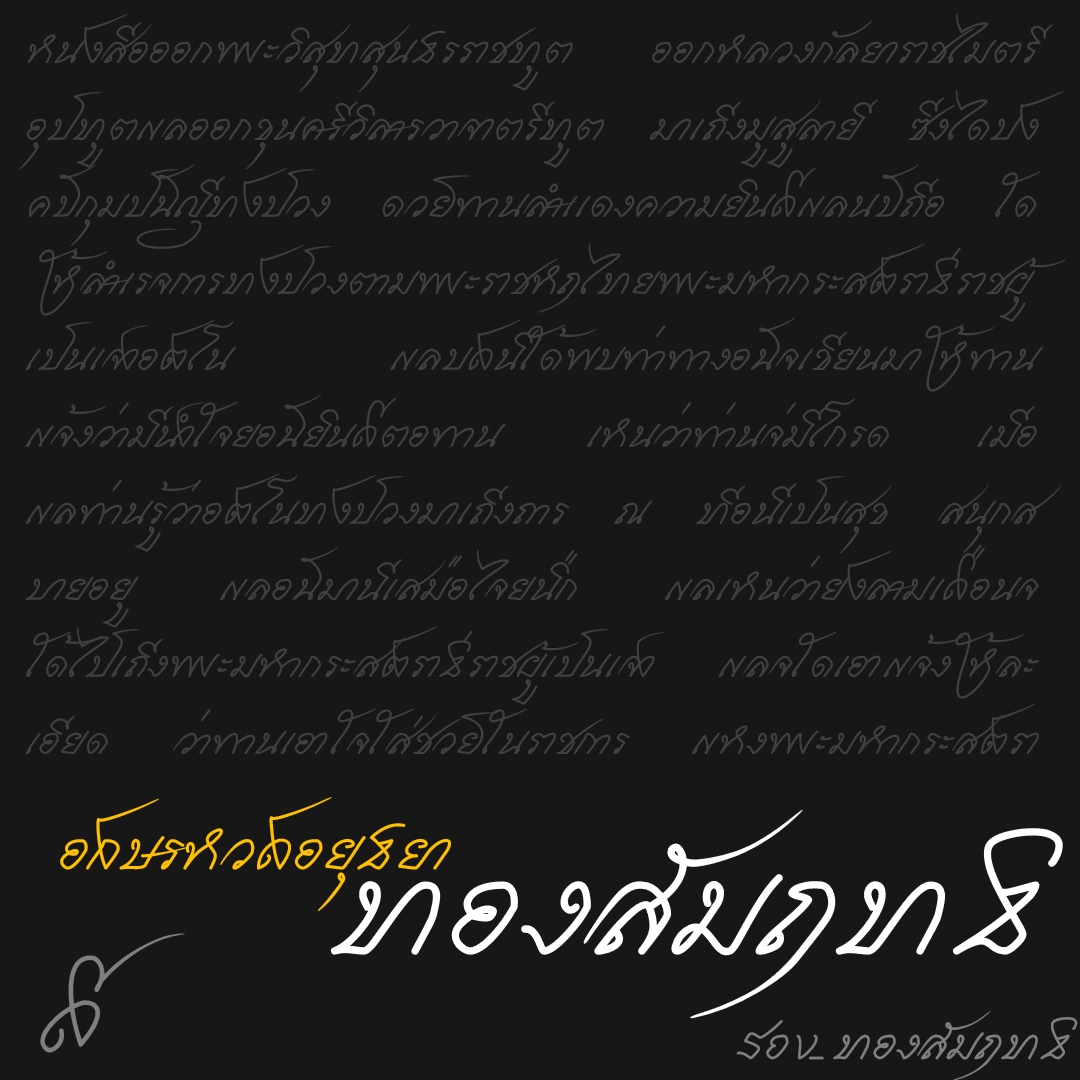
ฟอนต์ ทองสัมฤทธิ์
ฟอนต์ทองสัมฤทธิ์ ได้แนวคิดจากอักษรหวัด สมัยอยุทธยา โดดเด่นที่การรวบอักษร เชื่อมอักษร พยัญชนะ-พยัญชนะ พยัญชนะ-สระ พยัญชนะ-วรรณยุกต์ สระ-วรรณยุกต์ นอกจากนี้ยังมีการใช้พยัญชนะเดียวประสมสองรูป เช่น ในี (ในนี้) และอื่นๆ
ถ้าเอามาใช้กับแพนแกรม
ชื่อฟอนต์ : ทองสัมฤทธิ์
ฟอนต์ทองสัมฤทธิ์ ได้แนวคิดจากอักษรหวัด สมัยอยุทธยา โดดเด่นที่การรวบอักษร เชื่อมอักษร พยัญชนะ-พยัญชนะ พยัญชนะ-สระ พยัญชนะ-วรรณยุกต์ สระ-วรรณยุกต์ นอกจากนี้ยังมีการใช้พยัญชนะเดียวประสมสองรูป เช่น ในี (ในนี้) และอื่นๆ
คหสต.  อักษรตัวหวัดส่วนใหญ่เป็นการเขียนจากดินสอบนกระดาษถึงจะตวัดได้ จากอยุธยา 300ปีกว่า จะเหลือมาถึงปัจจุบันนั้นยากมาก เนื่องด้วยสภาพอากาศร้อนชื้นแบบบ้านเรา รวมถึงมอดปลวกอีก  หลักฐานที่พบได้มักอยู่ในที่อากาศเย็น เช่น ยุโรป และจีน ครับ
ลำดับการเขียนพวกไม้หันอากาศมีตัวสะกดนี่
เขาเขียนตัวสะกดก่อน แล้วค่อยเติมไม้หันอากาศข้างบนเหรอครับ
(รวมถึงการใส่เสียงวรรณยุกต์ของคำด้วย)
แล้วเวลาพิมพ์ต้องลำดับแบบนั้นไหมครับ
ตอนที่ทำฟอนต์ ก็มีคำถามนี้เหมือนกันครับ  เลยเอาตัวเองเป็นที่ตั้งว่า ถ้าเราจะเขียนคำว่า
- "ข้าพเจ้า" แบบเร็วๆ การเขียนไม้โท สระอา ช้ากว่า สระอา-ตวัดหางขึ้น  ผมก็จะเขียน ข สระอา-ตวัดหาง
- "ด้วย" ก็จะเขียน ด ว ย-ตวัดหาง
- "อัน" ก็จะเขียน อ น-ตวัดหาง
ผมสังเกตว่า อักษรตวัดหาง ใช้กับ ไม้โท และไม้หันอากาศ เท่านั้น เพราะเป็นอักษรสบัดหางยาว ต้องขยับมือเยอะกว่า
ถ้ามีคำถามแทรก ว่าเราเขียนคำว่า "กัน" ต้องลำดับว่า ก  ั  น ไม่ใช่หรือ แล้วจะรู้ได้ยังไงว่า จะใช้ น-ตวัดหาง
อยากให้ลองสังเกตุดูดีๆ ก่อนเราจะเขียนว่า "กัน" ถ้าเรามีสติดีอยู่ เราจะมีภาพในหัวก่อน หรือขณะที่เขียน ก.ไก่ แล้วว่า จะเขียน ไม้หันอากาศ แล้วตามด้วย น  ... แล้วก็อาจเปลี่ยนใจว่า เสียเวลาจัง เขียน น-ตวัดหางไปเลยละกัน
ส่วนเวลาพิมพ์ ให้พิมพ์ตามลำดับปรกติ เพราะถึงเราเปลี่ยนใจกระทันหัน ก็ไม่มีปุ่ม น-ตวัดหางให้กดจ้า ..เดี๋ยวฟอนต์จัดการสบัดหางและลบไม้โท ไม้หันอากาศ ให้เองครับ